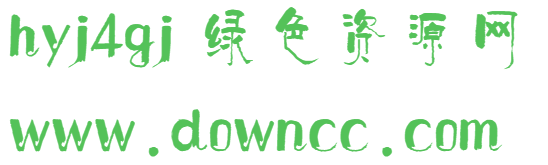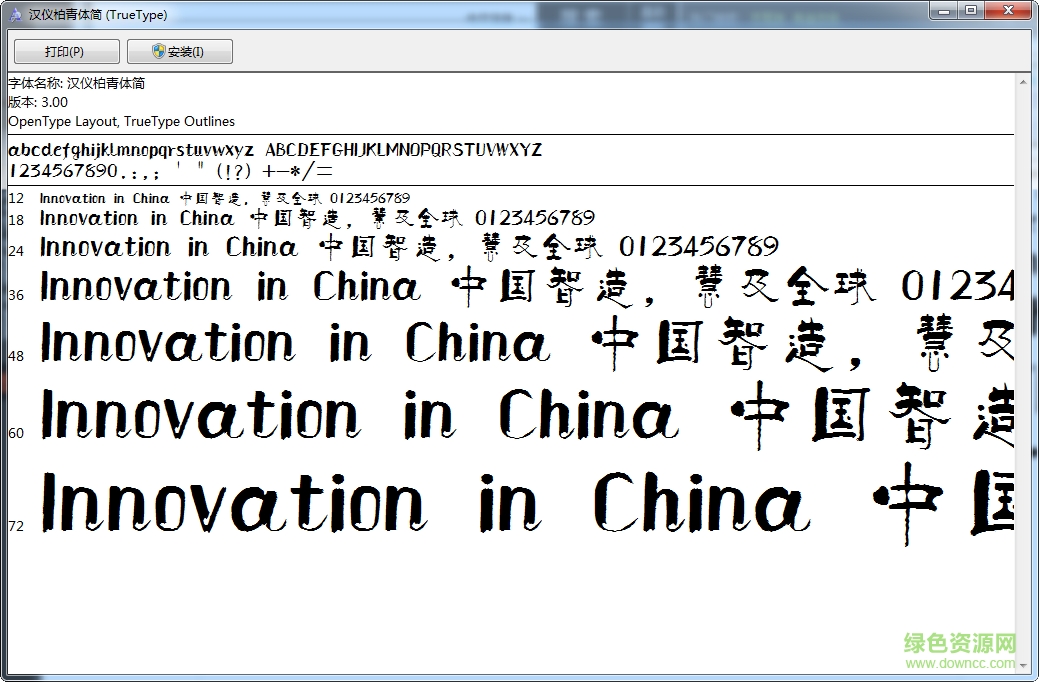
hyj4gj是什么字體?hyj4gj字體就是漢儀柏青體簡(jiǎn)體,這款字體修長(zhǎng)秀美,舒展自如,帶有潑墨感,整體看上去幽雅古典有氣質(zhì),有需要者歡迎在綠色資源網(wǎng)下載!
漢儀柏青體簡(jiǎn)是一款非常有個(gè)性的一款字體,字體效果比較有設(shè)計(jì)感,效果非常出眾,可以應(yīng)用于廣告設(shè)計(jì)、名片設(shè)計(jì)、包裝印刷、產(chǎn)品設(shè)計(jì)等領(lǐng)域!